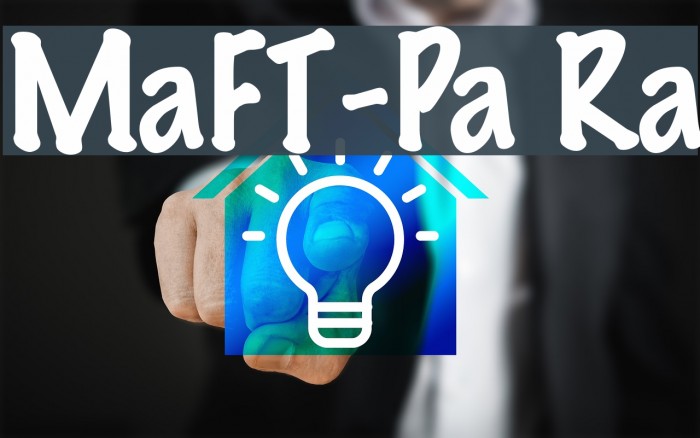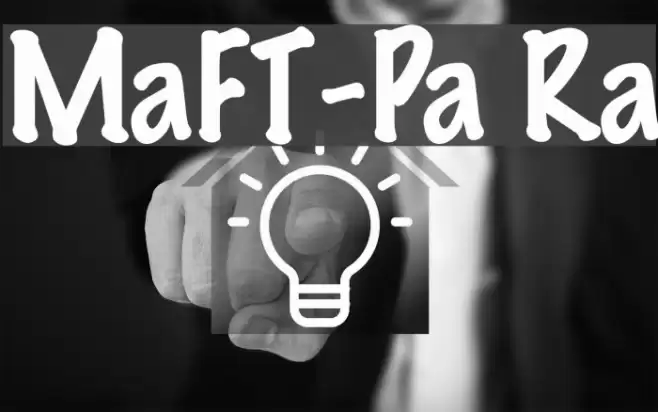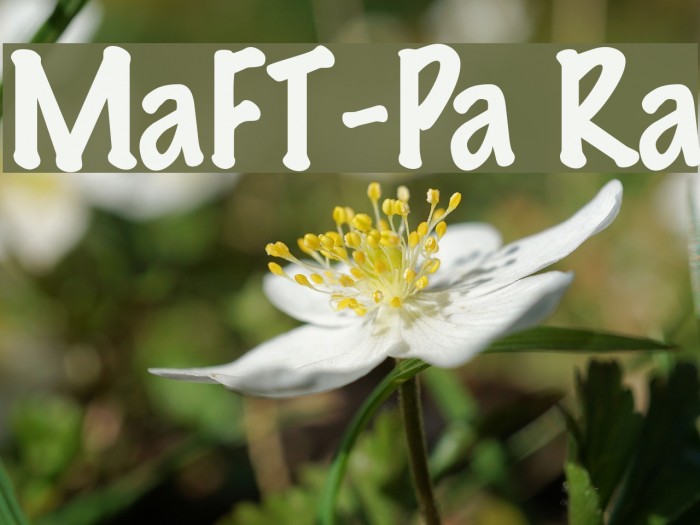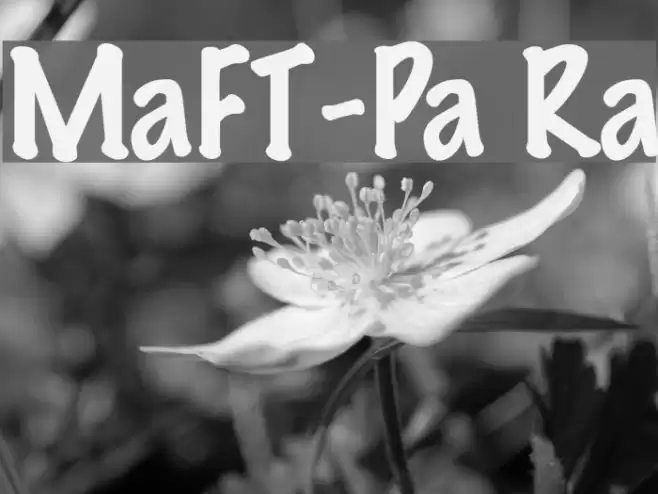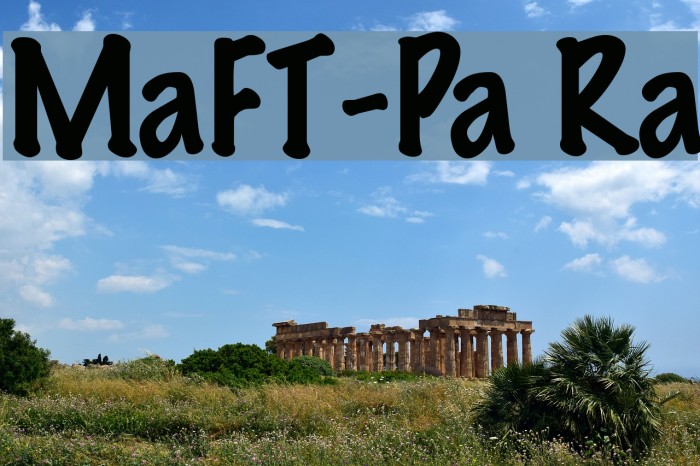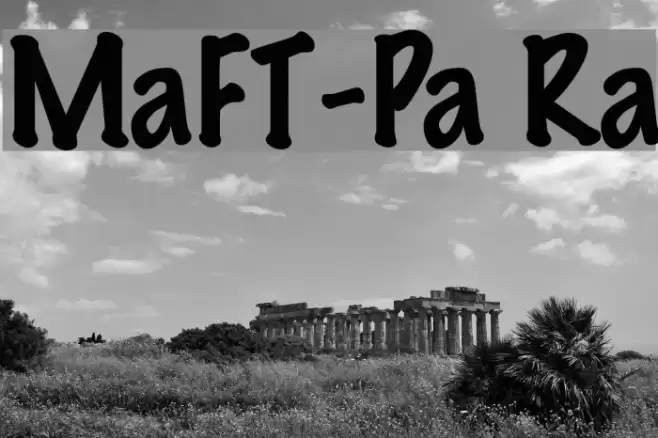
MarkerFeltThin-Plain Regular Font
| Caz de utilizare | Headlines, Logos, Informal Text |
| Proiecte propuse | Ideal for children's books, greeting cards, posters, and any project requiring a casual, friendly touch. |